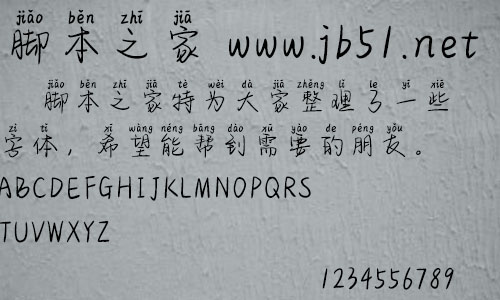
Aa今后我與自己流浪一款不錯(cuò)的藝術(shù)字體,由Aa字庫(kù)出品,字體筆觸纖細(xì),書(shū)寫(xiě)流暢,支持漢字和拼音同步輸入,具有很好的視覺(jué)感,適合應(yīng)用于藝術(shù)設(shè)計(jì)、平面宣傳設(shè)計(jì)、網(wǎng)頁(yè)設(shè)計(jì),書(shū)法字帖等領(lǐng)域,需要的朋友可以前來(lái)本站下載。